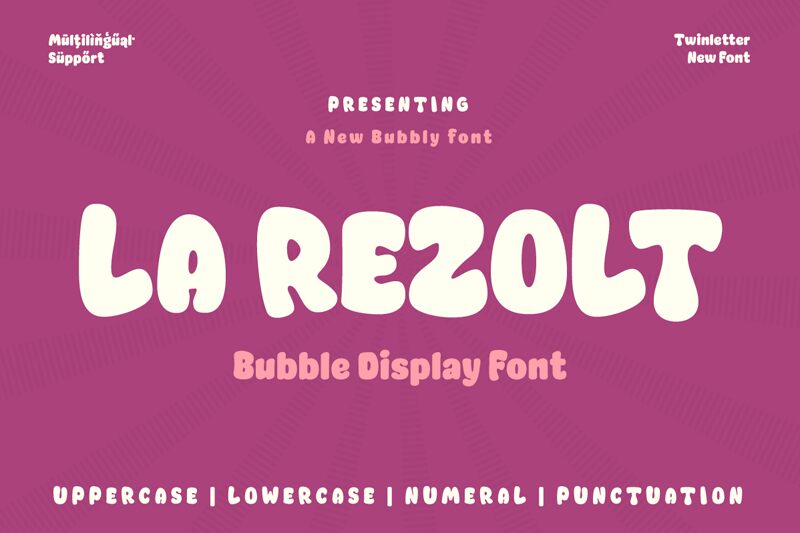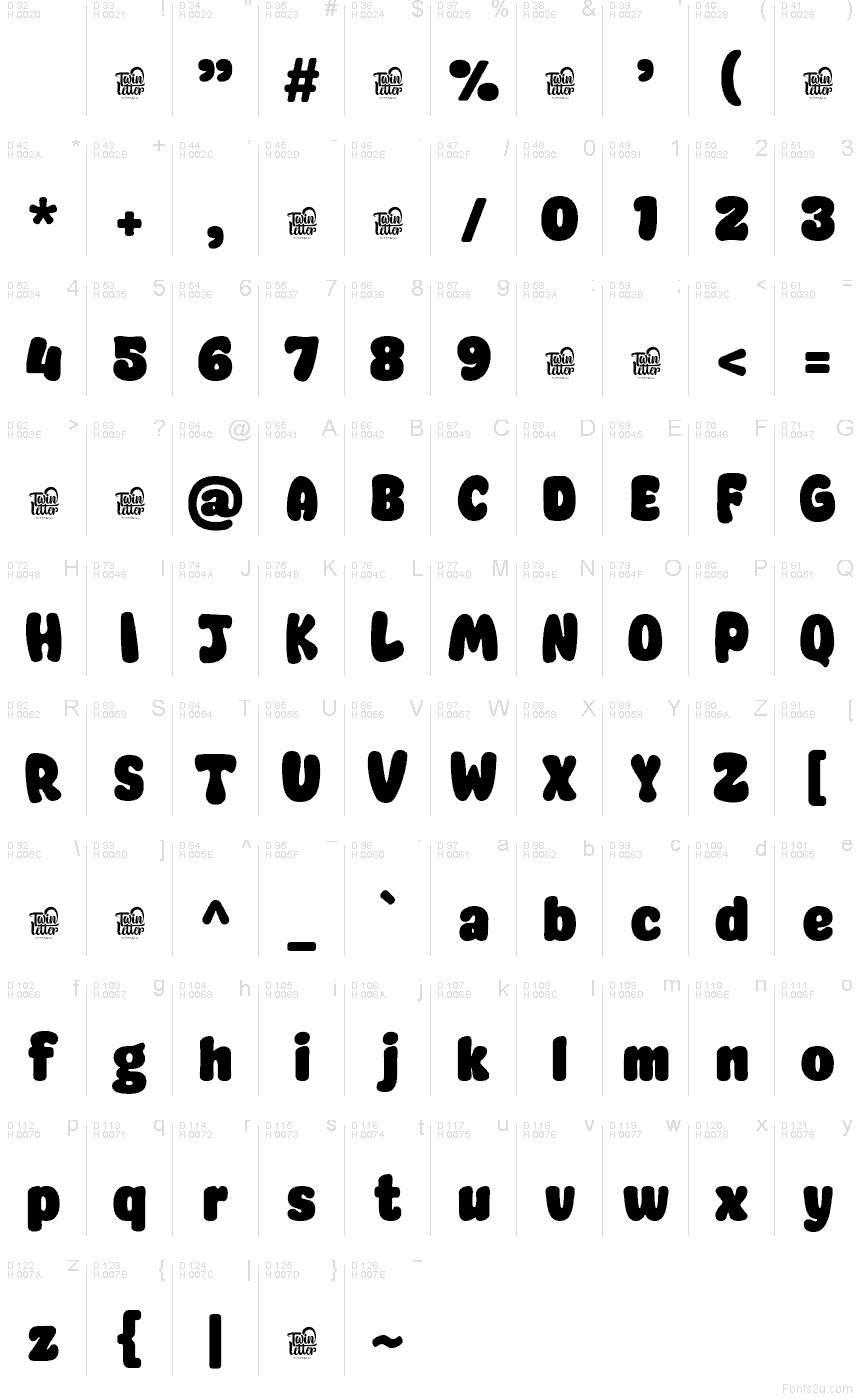
Pleine de fantaisie et de caractère, La Rezolt est une police display remarquable conçue par Twinletter. Ses traits gras et ludiques insufflent une belle dose d'énergie, captant instantanément le regard et attirant l'attention. Les formes uniques de ses lettres associent avec fluidité des courbes organiques à des angles vifs et marqués, créant ainsi une esthétique singulière qui fait naturellement le lien entre styles graphiques traditionnels et contemporains.
La polyvalence de cette police se révèle dans sa capacité à sublimer une large variété de projets, des titres percutants aux identités visuelles fortes, en passant par des publications captivantes pour les réseaux sociaux et des packagings dynamiques. Avec sa personnalité audacieuse inspirée de l'univers du cartoon, La Rezolt convient particulièrement aux créations qui cherchent à exprimer la joie, l'enthousiasme ou un dynamisme résolument jeune.